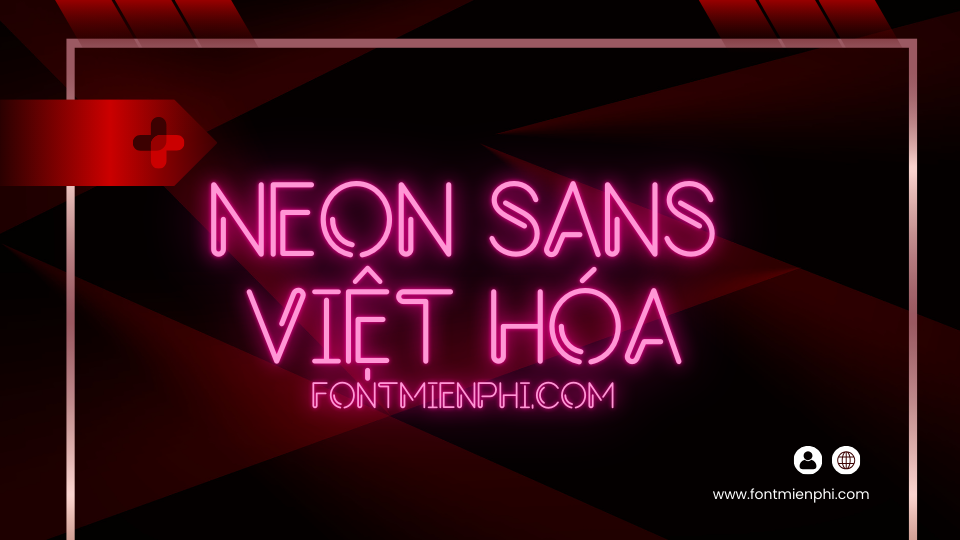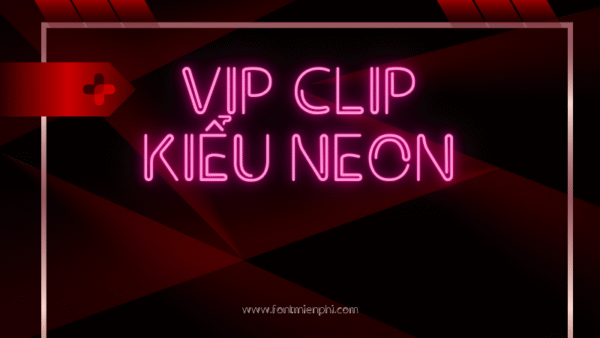
Font Việt hóa 1FTV VIP Neon Sans
Font chữ 1FTV VIP Neon Sans là một trong những lựa chọn tuyệt vời cho những ai muốn tạo dấu ấn đặc biệt trong thiết kế đồ họa. Với phong cách hiện đại và trẻ trung, font chữ này mang lại cảm giác năng động, phù hợp với nhiều lĩnh vực như quảng cáo, sự kiện, và thiết kế nội dung trực tuyến.
Đặc điểm nổi bật:
1. Thiết kế độc đáo: 1FTV VIP Neon Sans được thiết kế với các đường nét mềm mại, giúp tạo ra sự thu hút và dễ đọc. Điểm nhấn neon trong font chữ này mang lại cảm giác hiện đại và sống động, rất thích hợp cho các dự án cần sự nổi bật.
2. Hỗ trợ tiếng Việt: Một trong những ưu điểm lớn của font chữ này là khả năng hỗ trợ đầy đủ các ký tự tiếng Việt, bao gồm cả các dấu câu và chữ cái có dấu. Điều này giúp người dùng dễ dàng sử dụng trong các tài liệu và thiết kế có nội dung tiếng Việt.
3. Dễ dàng tùy chỉnh: Font chữ 1FTV VIP Neon Sans cho phép người dùng tùy chỉnh kích thước và màu sắc theo ý thích, giúp bạn linh hoạt hơn trong việc sáng tạo.
Với những đặc điểm nổi bật và tính ứng dụng cao, font chữ 1FTV VIP Neon Sans xứng đáng là sự lựa chọn hàng đầu cho những ai muốn tạo nên sự khác biệt trong các sản phẩm thiết kế của mình. Hãy trải nghiệm ngay hôm nay để cảm nhận sự khác biệt mà nó mang lại!